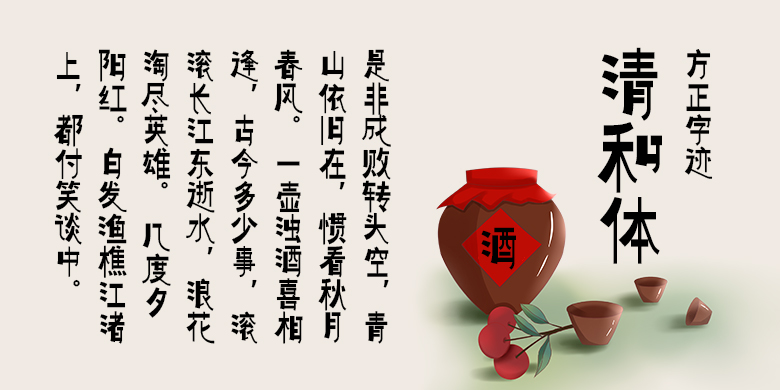
方正字迹-清和体
字体品牌: 方正字迹 设计师:周元庄 字体分类:创意字体 字体属性:精品字 字符集:大陆简体(GB2312-80) 发布时间: 2022
字体的结构特征,横细竖粗,撇弯捺直,字体之中,一横一撇具为天地。横划平,取清平之意;撇弯捺直,圆角收边,取圆润融合之意;伸、舒、展,字中乾坤,不外如是。